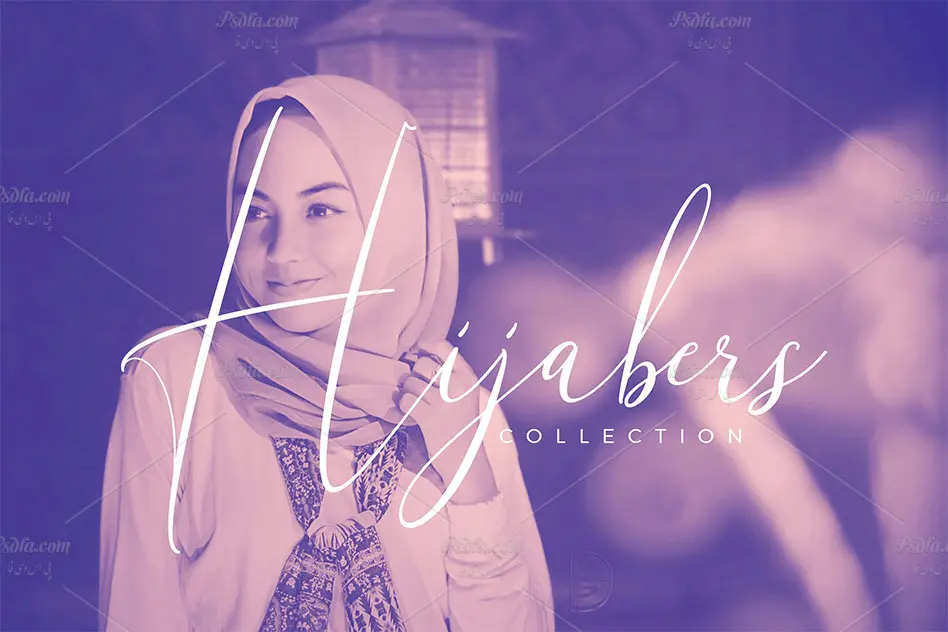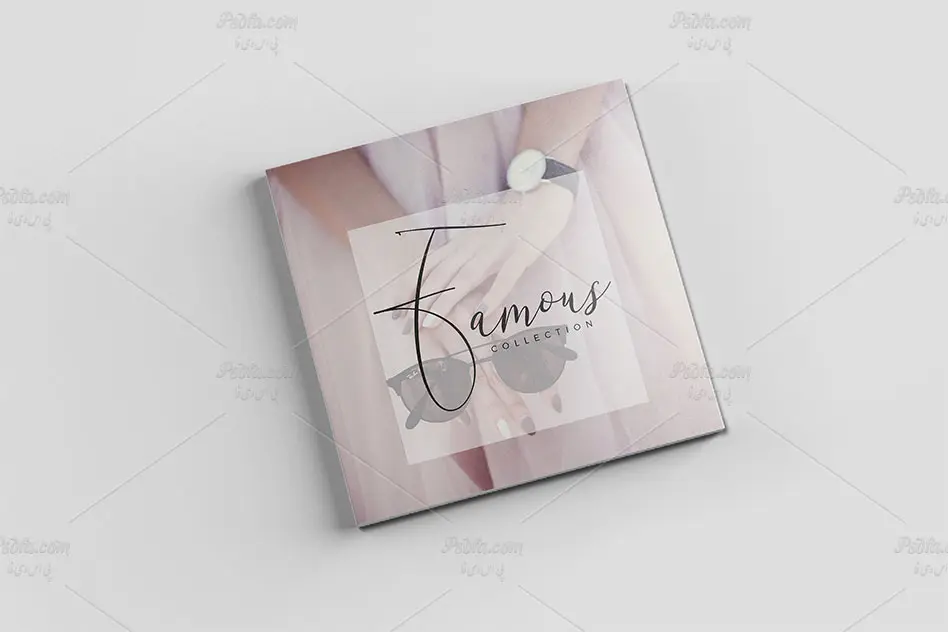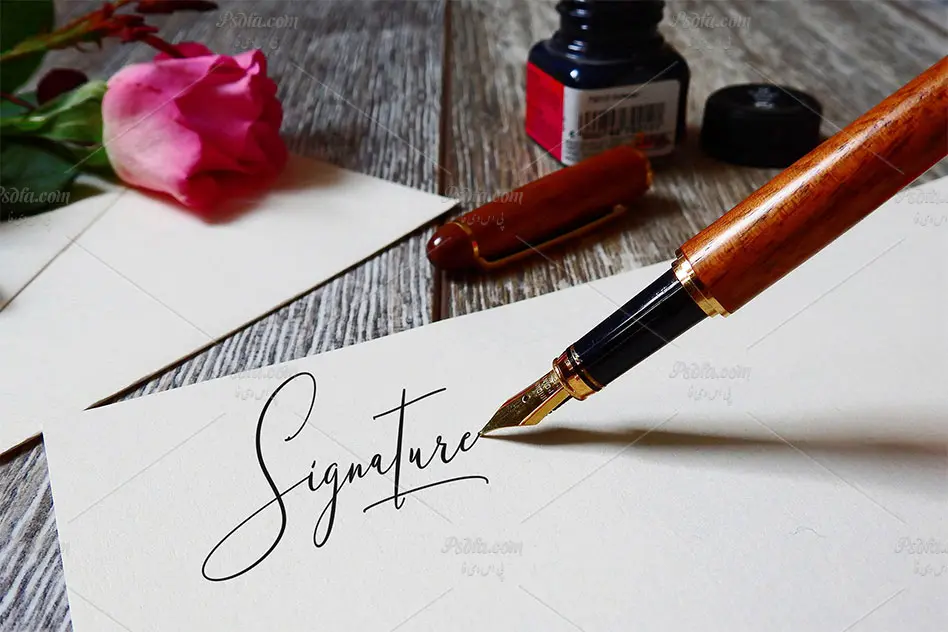
فونت انگلیسی امضاء
در این مطلب از سایت گرافیکی پی ای دی فا شاهد فونت انگلیسی امضاء مناسب برای طراحی و گرافیک می باشید. این فونت فوق العاده زیبا با دو فرمت ttf و otf در سایت قرار داده شده است که پس از نصب فونت ها در پوشه سیستم خود قادر به استفاده از آن ها در تمام نرم افزارهای گرافیکی و ویرایشگر متن از جمله نرم افزار فتوشاپ ، مجموعه نرم افزار آفیس و … می باشید. فونت ها در سه سبک متفاوت طراحی شده اند که بسته به نیاز خود می توانید از هر کدام استفاده کنید البته فونت Sensational Extra به صورت سمبل طراحی شده است که جهت تزئین طرح خود می توانید از آن نیز بهره مند شوید. از این فونت زیبا می توان در طراحی انواع کارت عروسی ، کارت تبریک ، کارت پستال ، طراحی پوستر و … استفاده نمود.